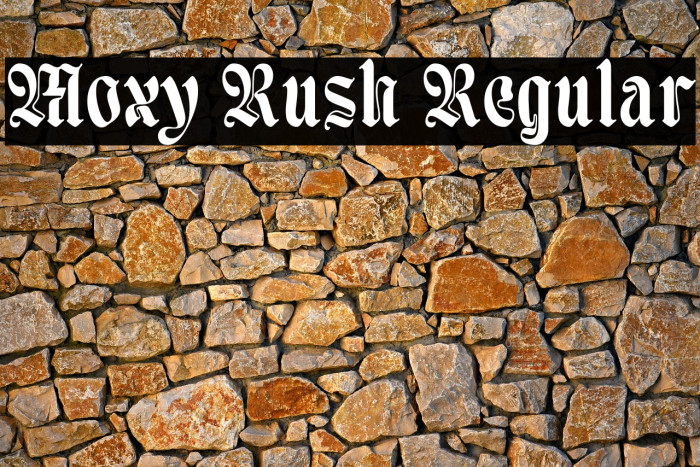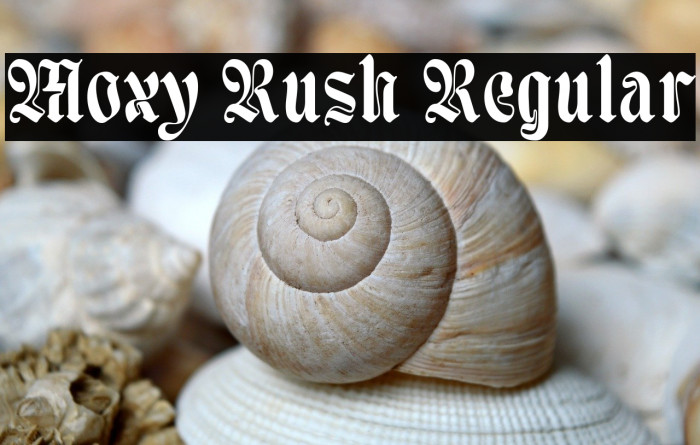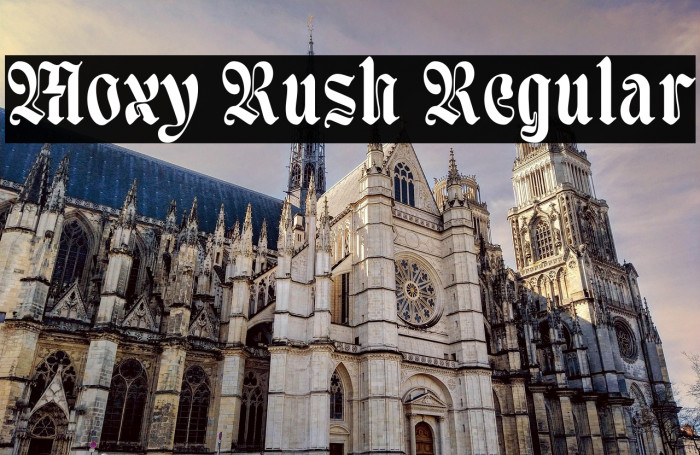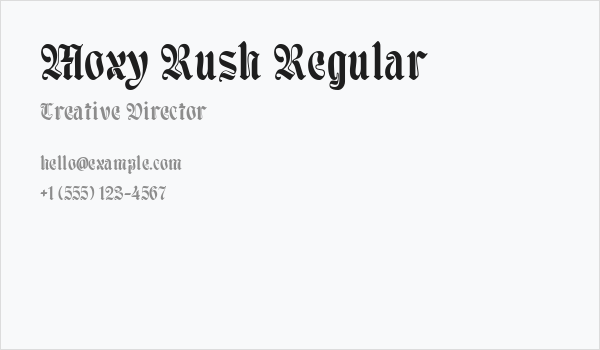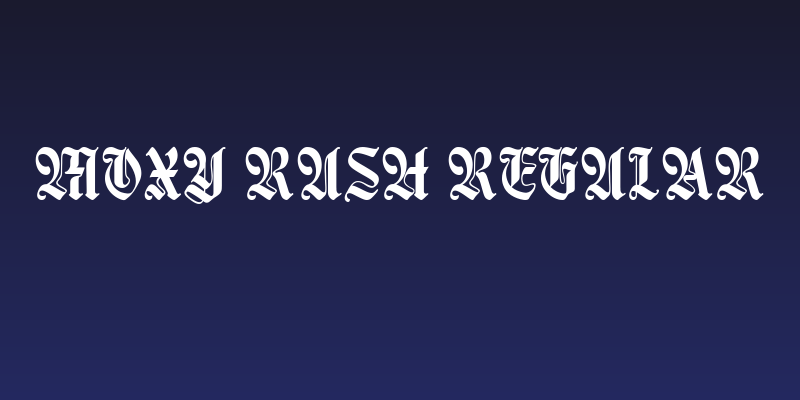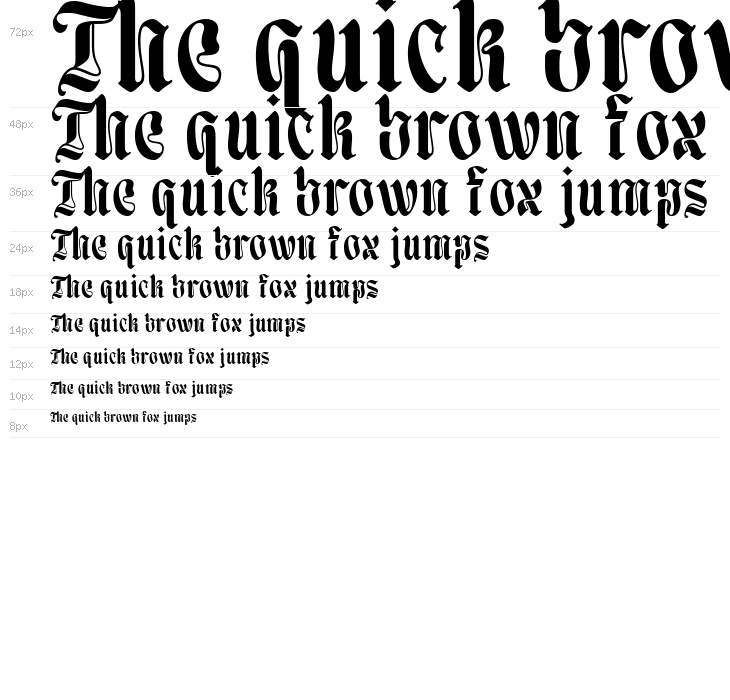
Moxy Rush Regular Font
✎ Gothic
| Stile generale | Gothic, Historic, Decorative |
| Progetti proposti | Ideal for projects requiring a historic or gothic touch, such as event posters, book covers, or branding for themed events. |